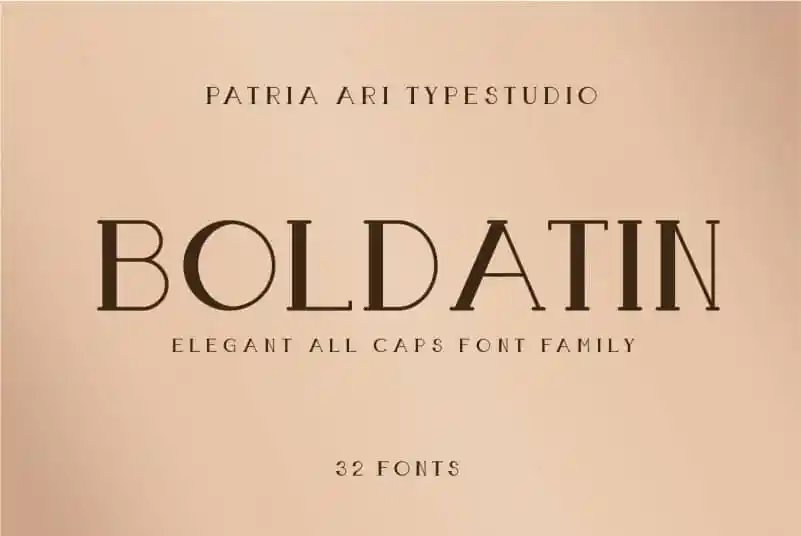
Boldatin Slab Display Font Family – Fonte Grátis
Boldatin Slab Display Font Family
A fonte Boldatin Slab Display é uma família de tipo com riscos que abrange diferentes estilos (regular, inclinado, apertado e inclinado apertado), totalizando 32 tipos de fonte com seis pesos para seus projetos como sinalização, pôster, bandeira e aviso. Esta fonte é perfeita para qualquer tipo de aplicação gráfica que exija um estilo forte e moderno, sejam eles materiais digitais ou impressos. Com uma variedade de opções, a Boldatin Slab Display permite um grau de personalização único, garantindo que seu design seja o mais atraente possível em qualquer projeto. Ela é especialmente adequada para elementos visuais que precisam ser notáveis e imediatamente reconhecíveis, como sinalizações urbanas, materiais de marketing ou até mesmo artesanato pessoalizado. Seja você um designer gráfico profissional ou criador de conteúdo casual, a Boldatin Slab Display está aqui para tornar seus projetos ainda mais impactantes e atraentes.